Nous avons travaillé avec la Société Jersiaise pour développer leur identité éditoriale.
Le vaste mandat éditorial de la Société exigeait une gestion sensible pour apporter un style cohérent et flexible.
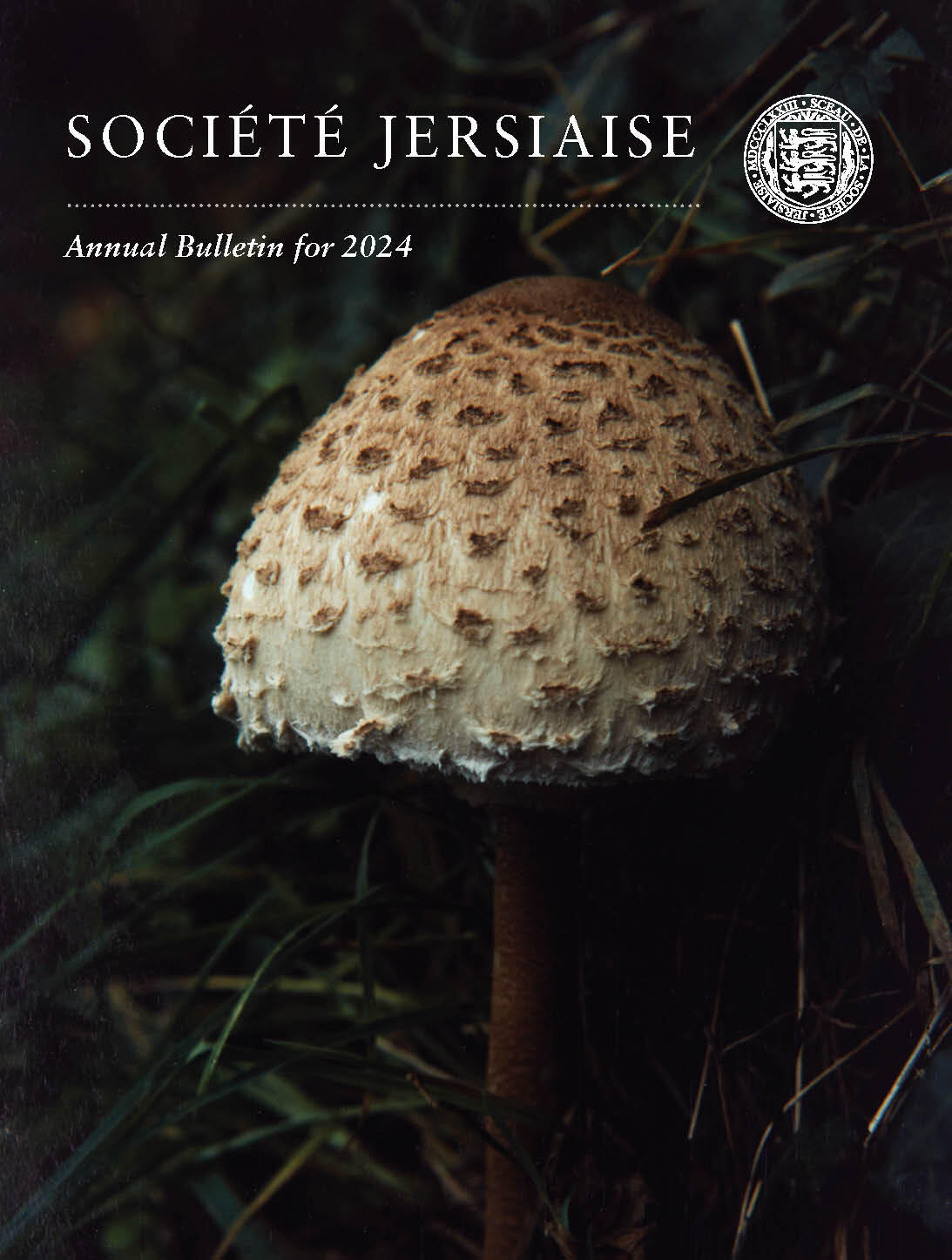
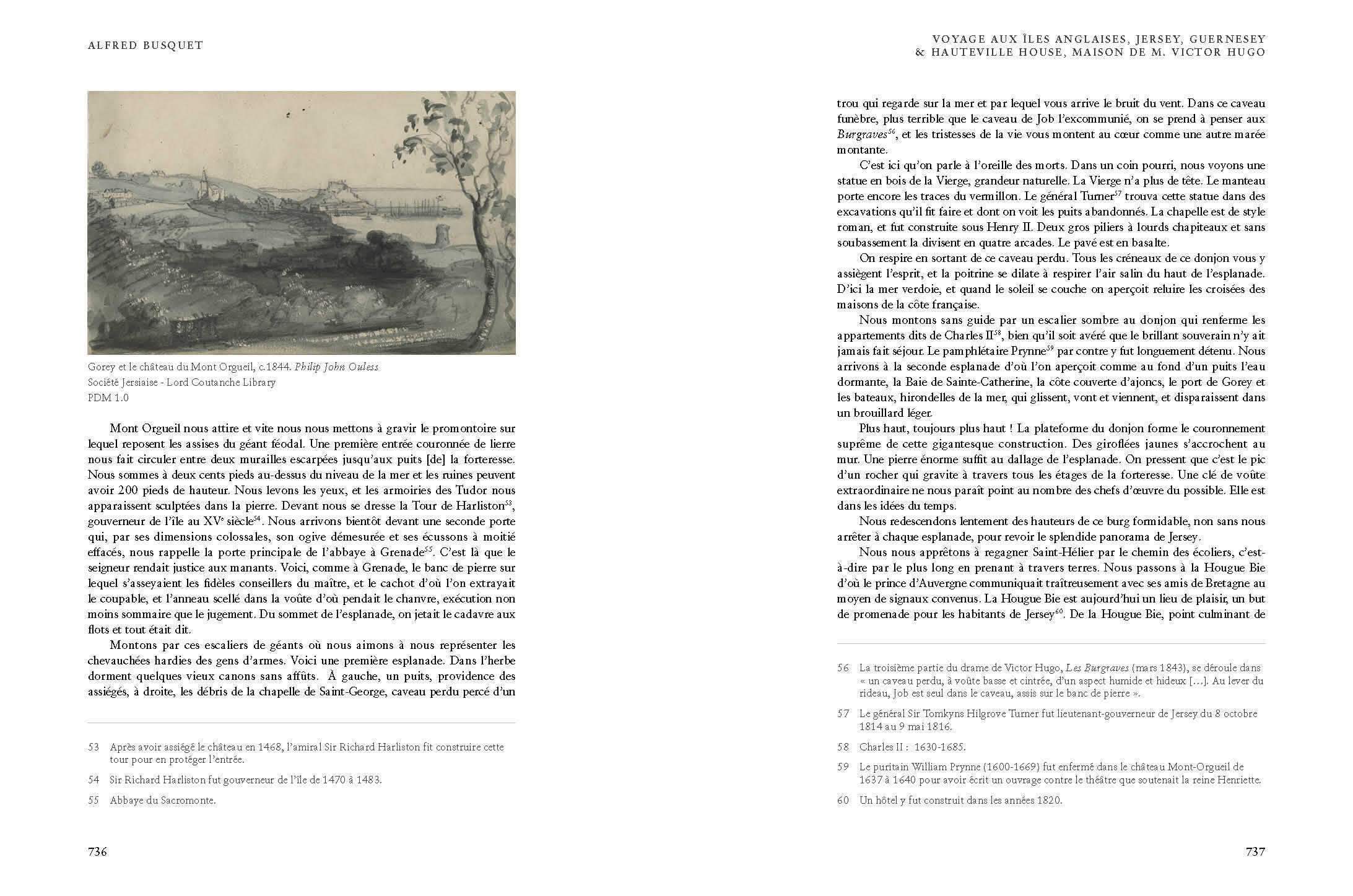
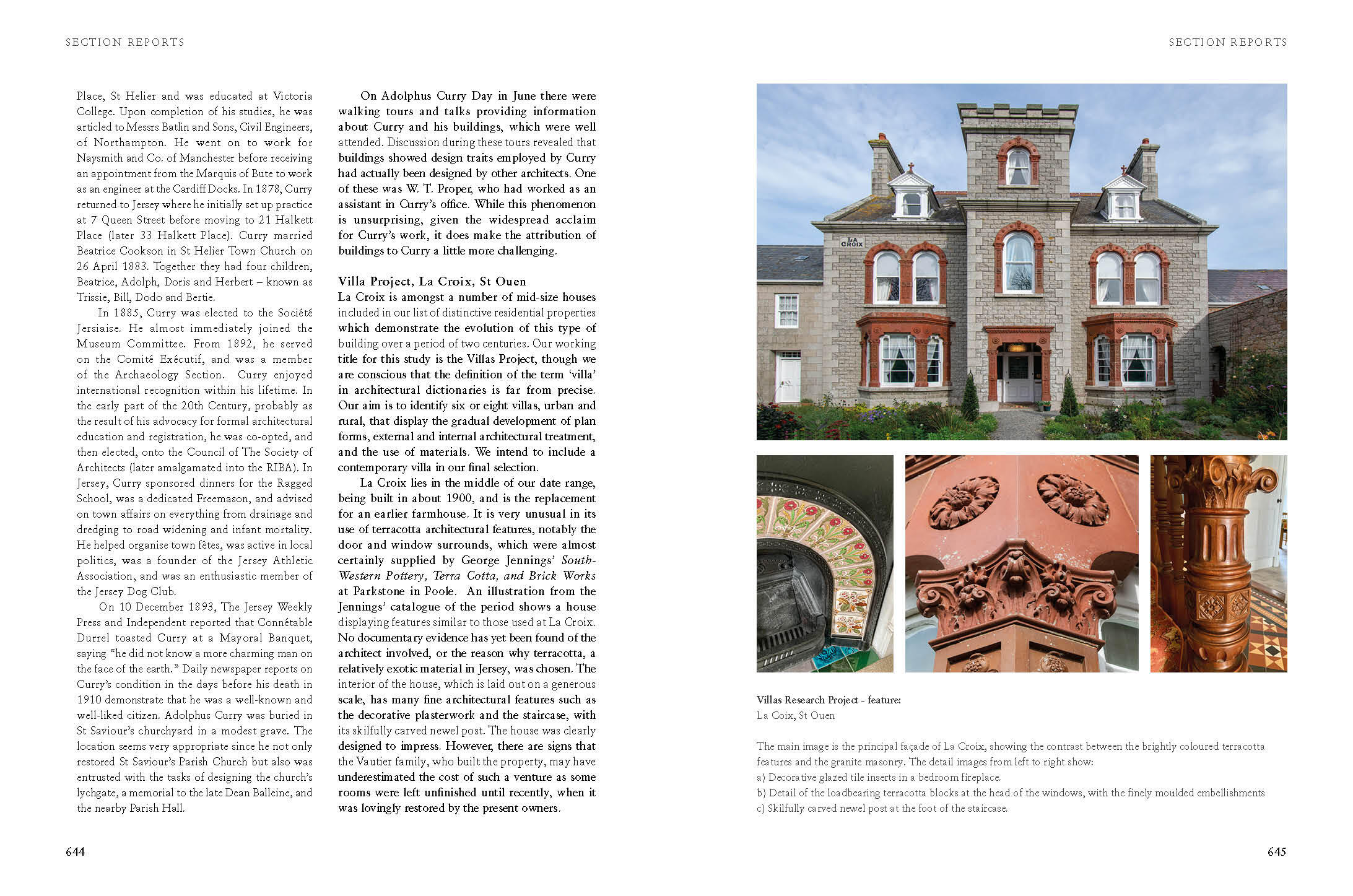
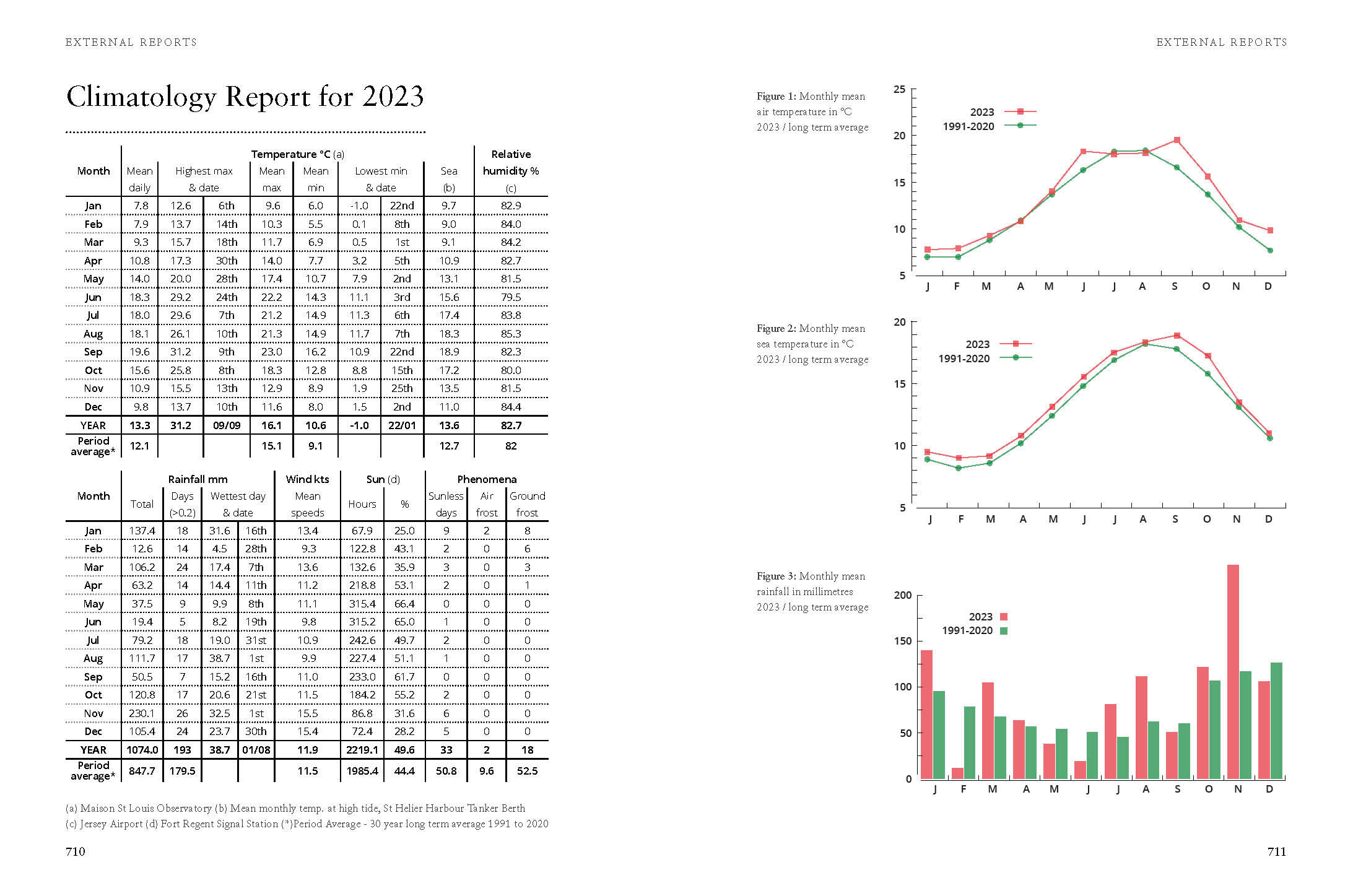
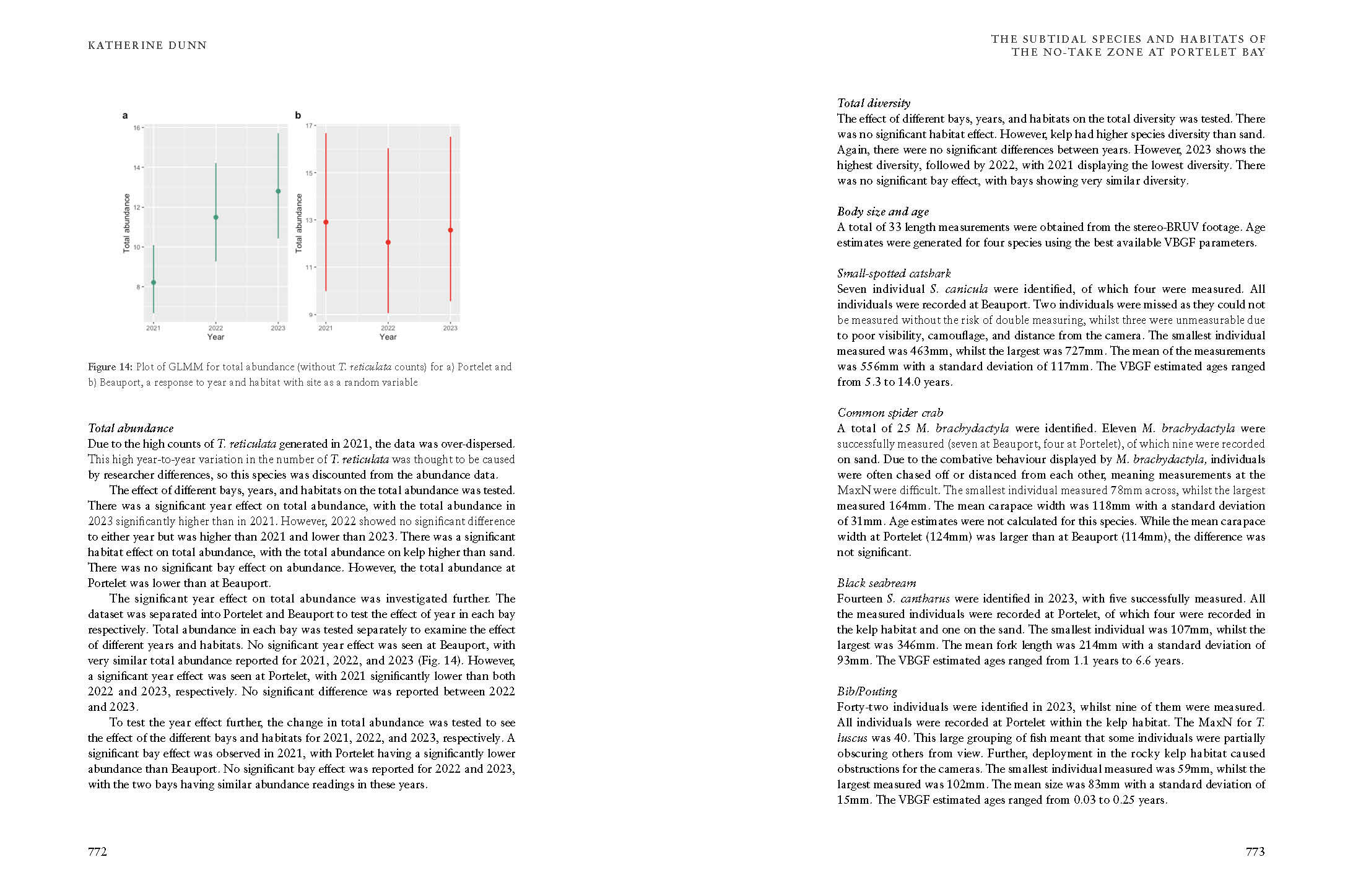
Il était nécessaire de respecter les 150 ans d'histoire et aussi présenter la Société comme une organisation de recherche active.
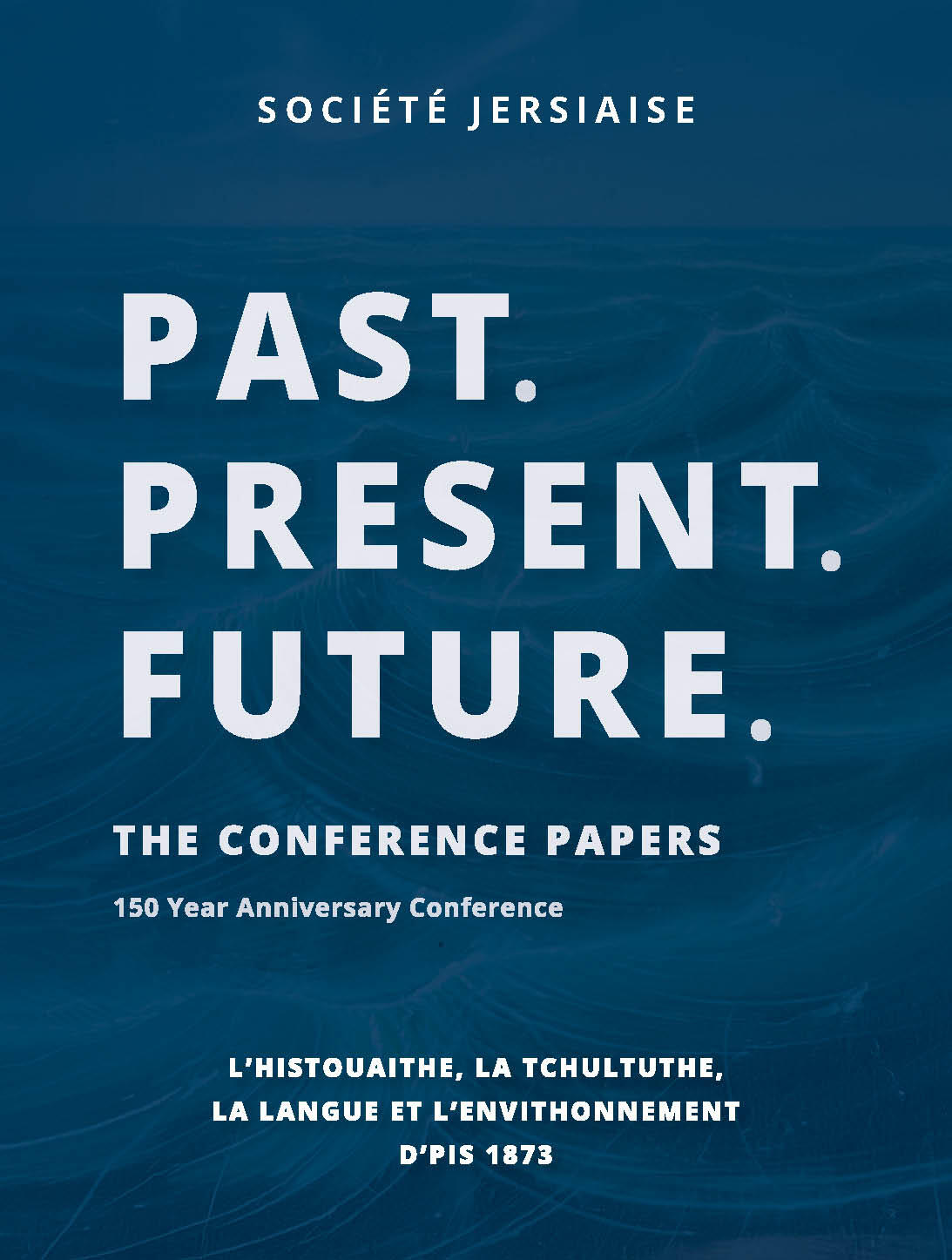
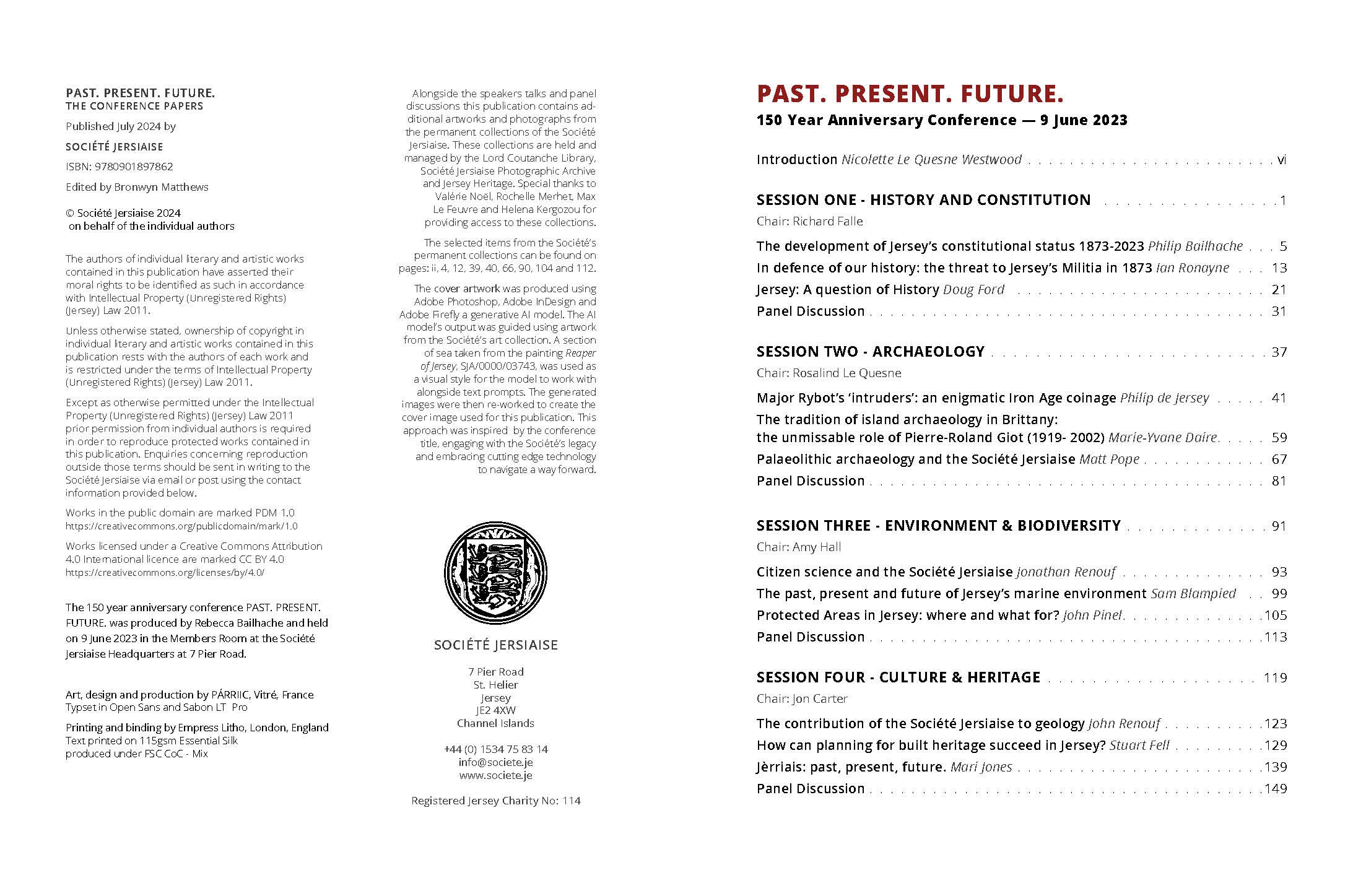
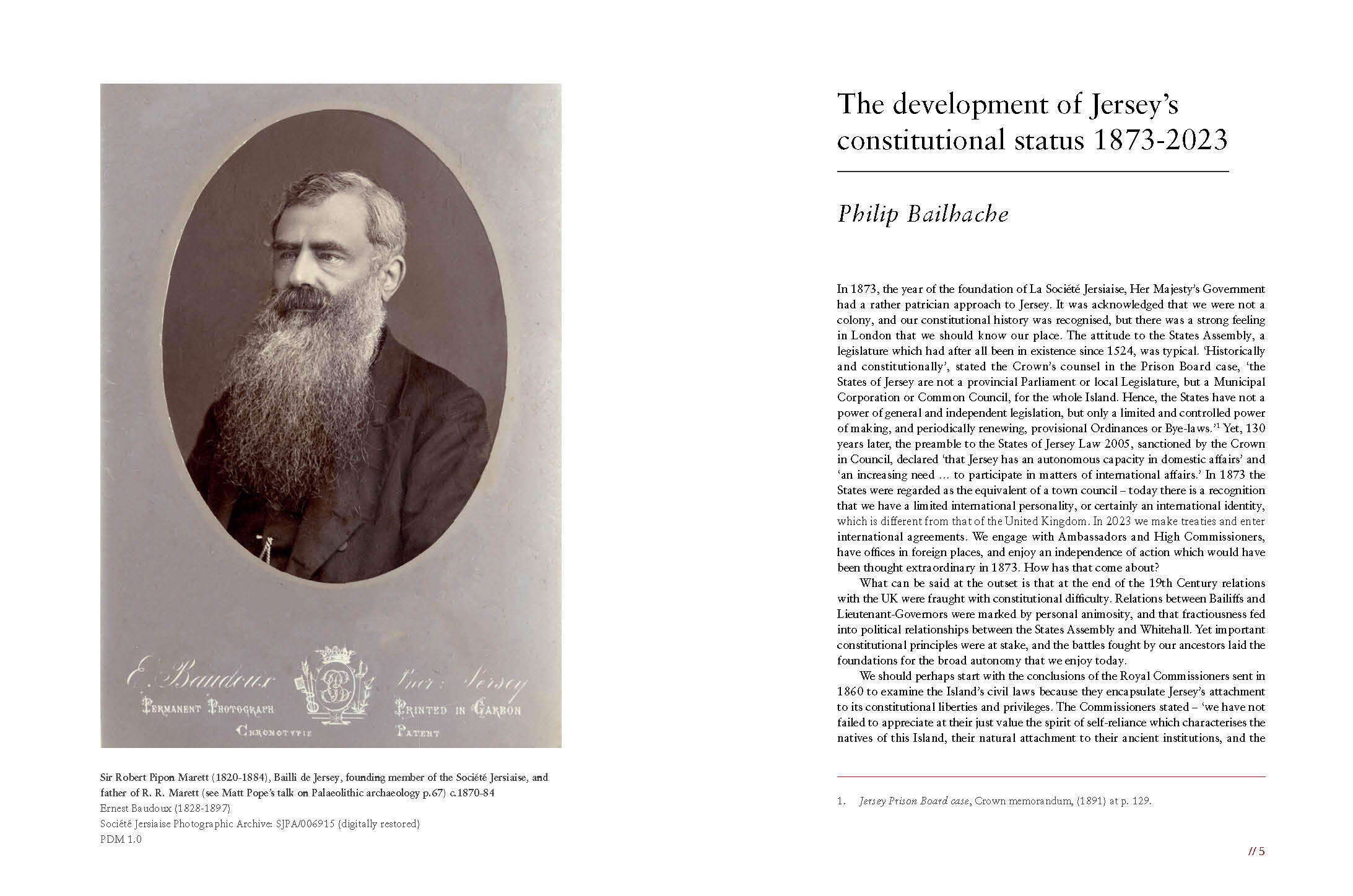
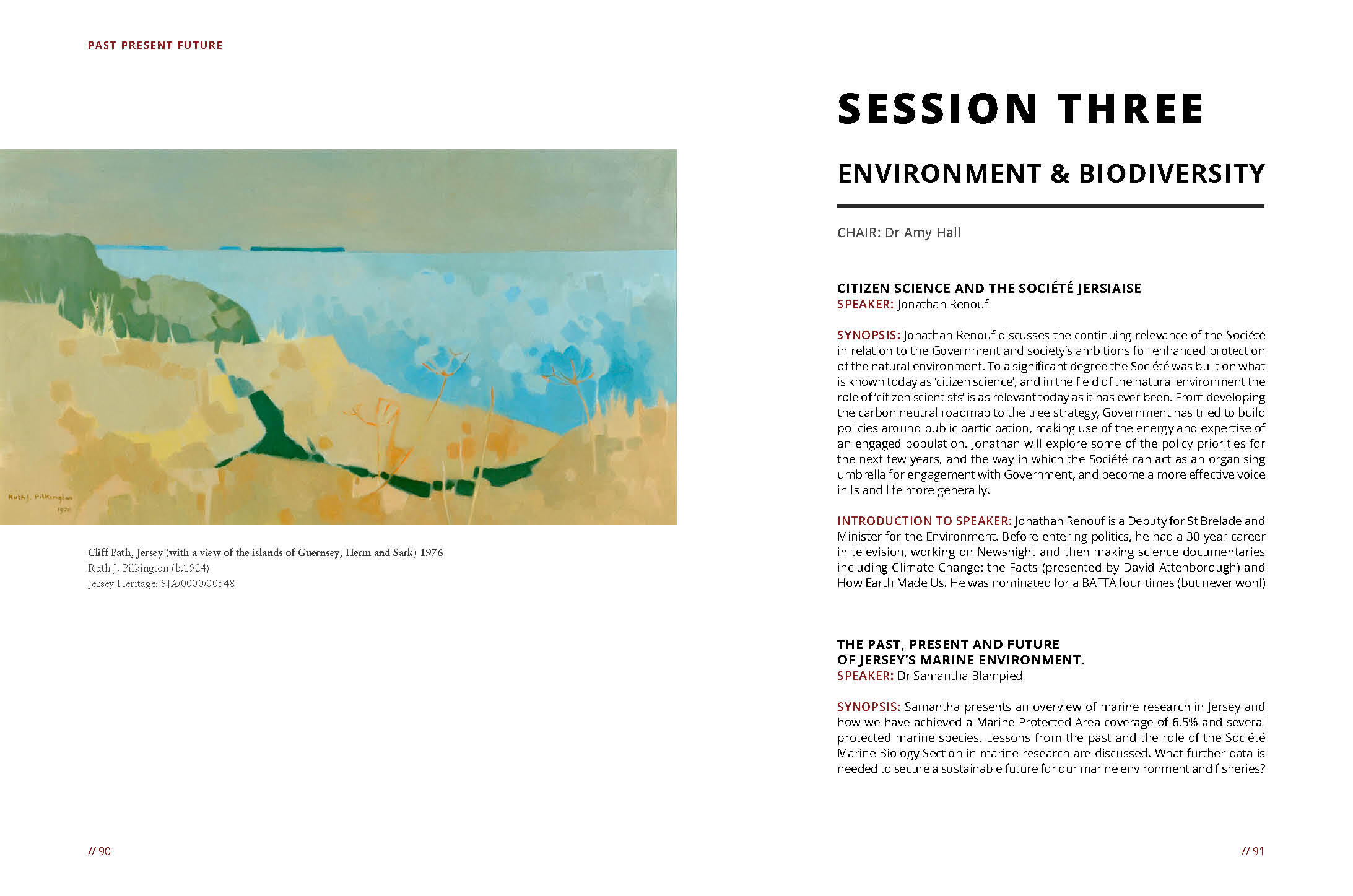
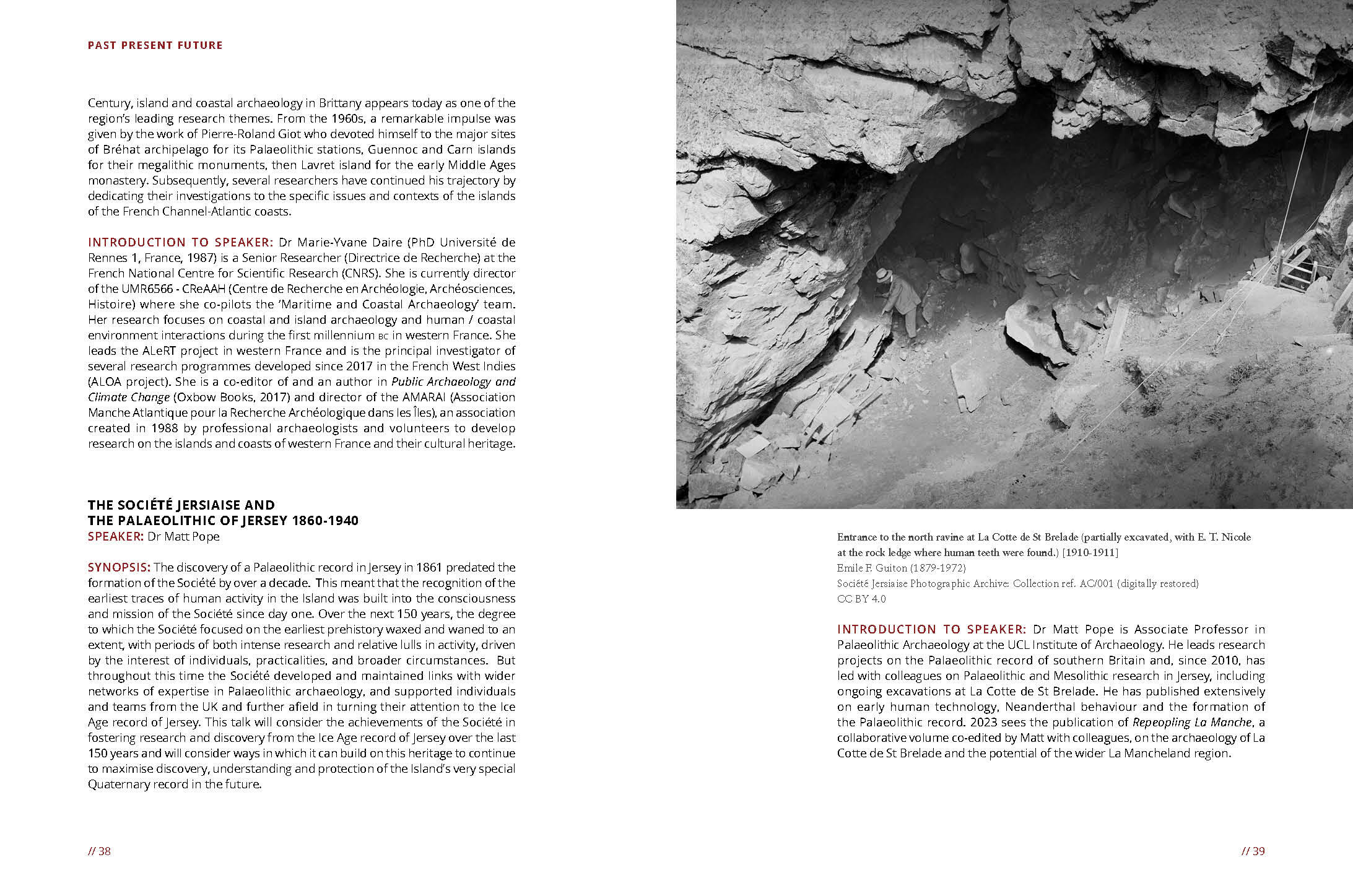
La Société avait également besoin d'un style moderne qui pourrait être utilisé dans les documents d'information et de promotion.
Certaines publications, comme les traductions de textes historiques, pourraient s’orienter davantage vers le traditionnel.
Les modèles ci-dessus ont été développés pour répondre aux besoins de publication réguliers de la Société, mais il est parfois nécessaire de faire quelque chose de spécial et d'unique...